Dịp Noel, tết nguyên đán sắp tới gần, để tặng bạn bè người thân chúng ta nên tạo những thiệp chúc. Để có được những tấm thiệp đẹp nhất, cần Font chữ đẹp viết lời chúc lên thiệp. Các bạn hãy chọn những Font chữ đẹp viết lời chúc sau đây để tạo thiệp tặng người thân nhé.
Thông thường để viết chữ trên các phần mềm soạn thảo, người dùng cần cài đặt bộ Font Việt hóa. Tuy nhiên những bộ font Việt hóa là chưa đủ phong phú và đa dạng nếu bạn có ý định tạo thiệp tặng người thân. Với bộ font chữ đẹp viết lời chúc sau đây, các bạn sẽ có ngay những tấm thiệp độc đáo nhất. Đây sẽ là món quà tuyệt vời nhất để tặng bạn bè, người thân trong các dịp như Noel hay Tết đấy.
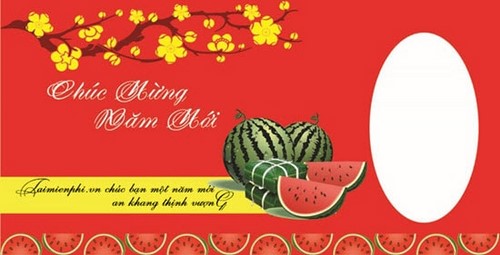
Thư viện font chữ đẹp viết lời chúc lên thiệp đẹp nhất - font chữ đẹp Candy Cane.
Th**ư viện font chữ đẹp viết lời chúc lên thiệp đẹp nhất:**
Mời các bạn tham khảo một số mẫu trong bộ Font chữ đẹp viết lời chúc.
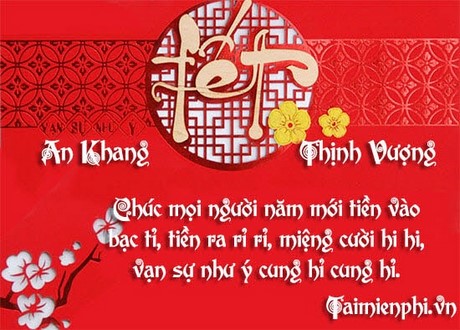
Thư viện font chữ đẹp viết lời chúc lên thiệp đẹp nhất - font chữ đẹp UTM Dai Co Viet
Thư viện font chữ đẹp viết lời chúc lên thiệp đẹp nhất - font chữ đẹp UTM Edwardian
Thư viện font chữ đẹp viết lời chúc lên thiệp đẹp nhất - font chữ đẹp UTM Novido
Thư viện font chữ đẹp viết lời chúc lên thiệp đẹp nhất - font chữ đẹp UTM Sloop
Nếu muốn tạo những tấm thiệp Tết, người dùng có thể tham khảo những lời chúc năm mới hay nhất. Sử dụng các font chữ đẹp viết lời chúc bằng những lời chúc năm mới hay và ý nghĩa sẽ là món quà lớn nhất cho những người thân yêu của chúng ta. Bạn đã có đầy đủ bộ font chữ đẹp viết lời chúc, những lời chúc hay, cách tạo thiệp ... Vậy thì còn ngại gì mà không bắt tay vào tạo những tấm thiệp đẹp nhất ngay bây giờ.